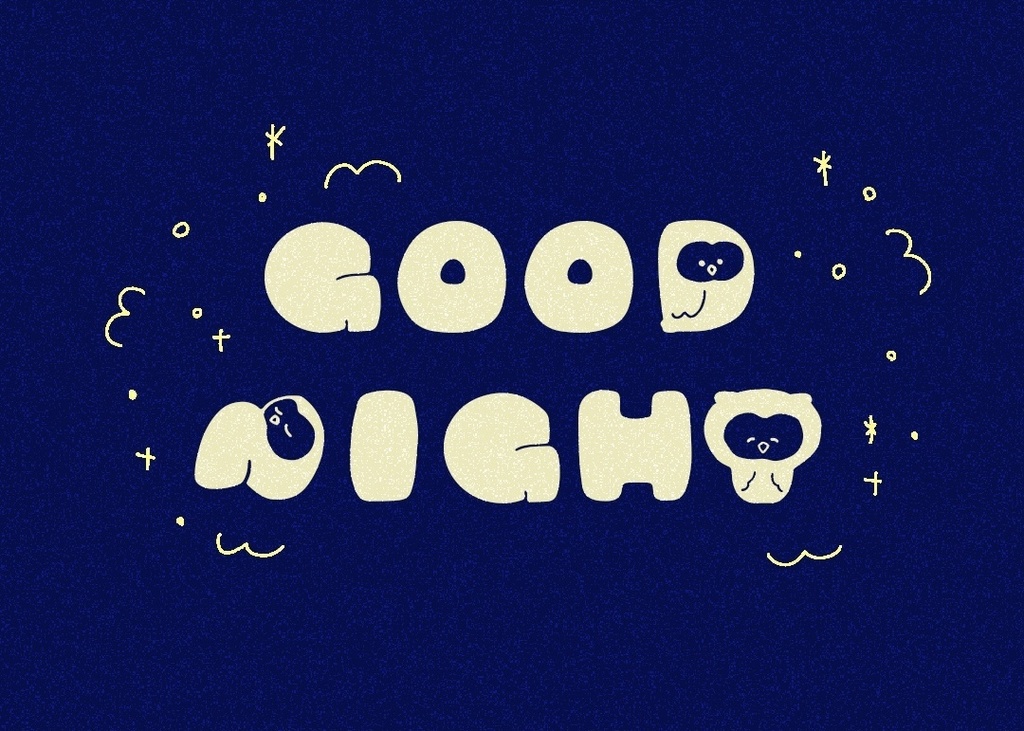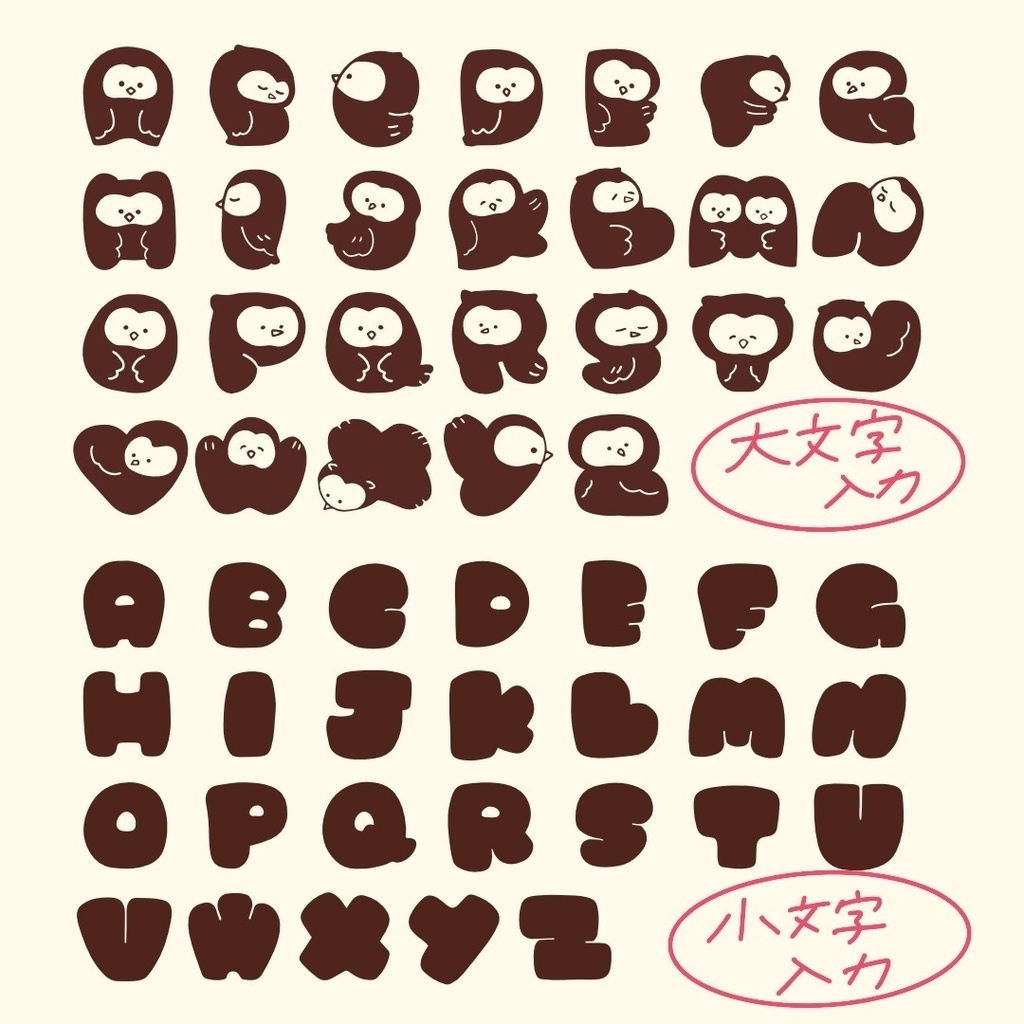
フクフクフォント
fukufuku(フクフク)フォントは、ふくふくとしたフクロウをモチーフにした手書きフリーフォントです。 大文字にはフクロウアルファベット、小文字にはフクロウアルファベットに合わせて使いやすいふっくらなアルファベット大文字を収録しています。 <使い方> フクロウたちとふっくらアルファベットを合わせて使ったり、それぞれ単体で使っても可愛いタイトル向けのフォントです。 <フォント形式> OpenType < 動作環境>Mac OSシステムでの動作確認済みです。 <ご利用規約> *こちらのフォントは個人利用、商用利用(印刷物・ゲーム・アプリ・映像・動画・ロゴ・同人作品など)問わずにお使いいただけるフォントです。文字の加工や変更も可能です。 *このフォントの著作権は放棄しておりません。フォントファイルを二次加工・再配布・再販売などは禁止しております。 *当フォントを使用した際に発生した機器およびソフトウエアの故障、誤動作、誤出力、ウイルスへの感染などに関して責任を負わないものとします。 本ファイルは武蔵システム(http://opentype.jp/)の(OTEdit for Mac)を使い作成しました。